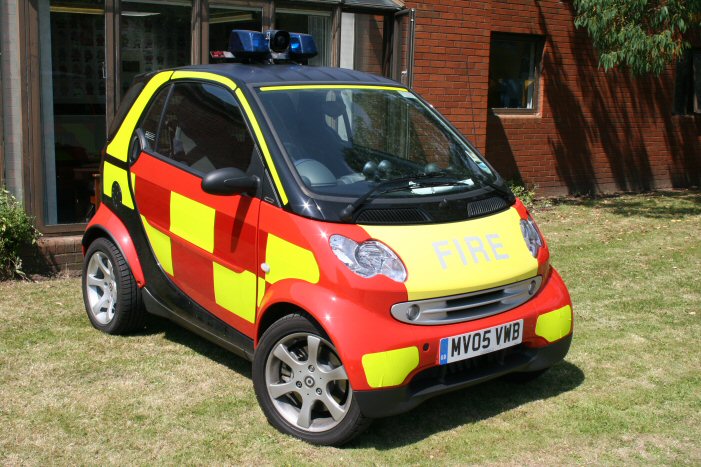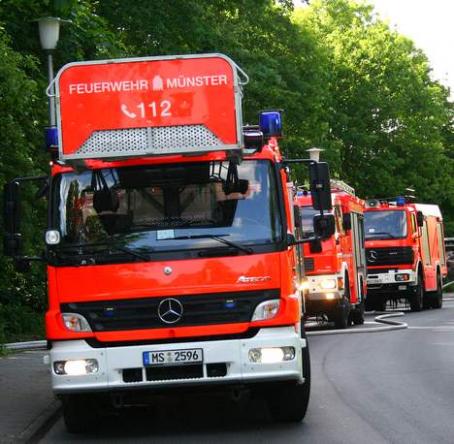
***TaTü—TaTa*** Beschriftung von Einsatzfahrzeugen.
… So viele Verwechslungsmöglichkeiten bestehen bei einem großem roten Auto mit Blaulicht eigentlich nicht. Außerdem sind andere Verkehrsteilnehmer nur verpflichtet sofort freie Bahn zu schaffen, wenn Blaulicht und Einsatzhorn gemeinsam verwendet werden (§ 38, StVO). Aus diesem Grunde werden auch vermehrt Frontblitzer im Kühlergrill verbaut, damit PKW-Fahrer einen LKW im Einsatz hinter ihnen wenigstens optisch besser wahrnehmen können.
Verwechslungsmöglichkeiten sind eher gering, richtig. Es gibt aber immer noch sehr viele Einsatzfahrzeuge ohne Frontblitzer, da ist es durchaus sinnvoll, wenn dich gerade im Stadtverkehr das Wort FEUERWEHR im Rückspiegel anschreit. Die akustische Ortungsmöglichkeit ist bei dem abgehackten Ton der deutschen Einsatzfahrzeuge eh schwierig …
Da hat mich ja folgende Aussage regelrecht angesprungen:
Das Design britischer Fahrzeuge erinnert an alles möglichem nur nicht Feuerwehr, oder irre ich mich?
Das trifft nur auf den ersten Blick zu, man gewöhnt sich extrem schnell um. Und die Farbgebung hat hier m.E. einen großen Vorteil: die gelb reflektierenden Kacheln sind Teil des Designs aller Einsatzfahrzeuge. Feuerwehr ist rot mit gelben Kacheln, die Krankenwagen in den East Midlands sind grün mit gelben Kacheln und die Polizei ist blau mit gelben Kacheln. Der Erkennungswert »Einsatzfahrzeug« ist damit extrem hoch – und das ist ja eigentlich auch richtig so, denn was genau für ein Einsatzfahrzeug das ist sollte zunächst mal von sekundärer Bedeutung sein.
Die Feuerwehr Münster hat es so gelöst, dass sie im Rückspiegel gar nicht erkennbar ist:
Die akustische Ortungsmöglichkeit ist bei dem abgehackten Ton der deutschen Einsatzfahrzeuge eh schwierig …
Kurzgefasst es geht darum, dass es früher neben der »Berliner Abstimmung« (Tatü–Tata) noch eine andere Klangfolge gab, die sogenannte »Dresdner Abstimmung« (Taatüü–tatü–tatü–tatü).